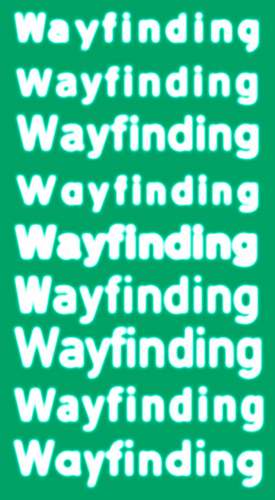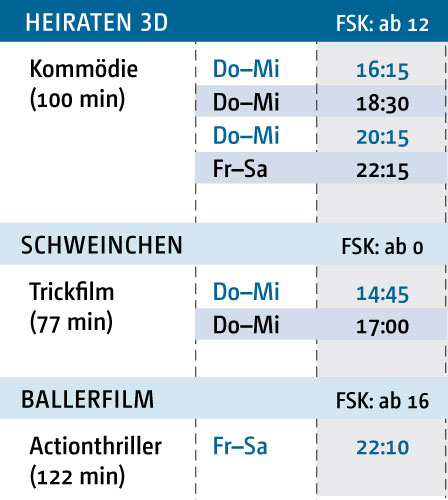
Phänomen Alterssehschwäche
Inwiefern muss man die Standardfloskel berücksichtigen, die bei jeglicher Art von Text unter 10pt wie aus der Pistole geschossen kommt?
»Aber die Älteren können das ja gar nicht lesen!«
Können ältere Menschen oft wirklich schlechter Text erkennen, oder müssen die einfach nur mal wieder zum Optiker? Ich kann mich da irgendwie schlecht reinversetzen. Das Gehirn verarbeitet die optischen Informationen doch genauso wie bei einem 20-Jähirgen – würde ich mal behaupten.
Natürlich kann der Text einmal kleiner wirken, wenn man stärkere Gläser hat – aber das betrifft ja nicht nur die Senioren.
Ich möchte zum Beispiel unsere Kinoprogramm-Handzettel komplett umstrukturieren in Tabellenform, also jede Spielzeit für jeden Tag einzeln aufführen. Gesetzt in Univers Condensed auf 8pt. Immerhin muss ich auch fast 250 verschiedene Spielzeiten unterbringen bei bis zu 20+ verschiedenen Filmen (variiert natürlich).
Ich bin auch schon sehr zufrieden. Vorher wurde alles abgekürzt wie
»tägl. 14:45, 16:45 & 18:45 Uhr, Mittwoch nur 15:45 Uhr!«.
Sieht nicht nur etwas unelegant aus, sondern führt auch zu Missverständnissen, da die Kinospielwochen immer Donnerstags anfangen, nicht Montags. Aber es hagelt natürlich bedenken, dass die älteren Leute das nicht erkennen können.
Ich habe mich dazu noch nicht konkret geäußert und will auch nicht unbedingt draufhämmern, dass die Senioren ohnehin keine relevante Zielgruppe darstellen. Würde lieber die Bedenken aus dem Weg räumen.
Barrierearm gestaltete Printprodukte sind nicht eindeutig definiert. 8 pt. condensed ist aber definitiv zu kleinteilig für Leute mit Altersweitsichtigkeit. Es gibt Brillen, die diese Sehschwächen simulieren können, das könnte dir helfen. Ich habe die Erfahrung gemacht, dass offene Buchstabenformen wie bei Lucida Sans gut gehen, wenn sie nicht zu knapp gesetzt werden und die Seite eine übersichtliche Struktur hat. Wer Schriftgrößen unter 10 pt nicht lesen kann, wird eh ein Hilfsgerät zu hause haben, also bist du in dem Korridor gut aufgehoben. Bei >10pt springen sogar die meisten Normalsichtigen ab, weil es nicht gut lesbar ist.
Die Stadt Münster hat hierzu einen Ratgeber herausgegeben:
Das Gehirn verarbeitet die optischen Informationen doch genauso wie bei einem 20-Jähirgen – würde ich mal behaupten.
Natürlich kann der Text einmal kleiner wirken, wenn man stärkere Gläser hat – aber das betrifft ja nicht nur die Senioren.
nur sieht man als "fehlsichtiger" nicht dinge schlicht kleiner. sondern beispielsweise unschärfer. guck mal in den autobahn-thread.
und stell dir das jetzt mal in 8 punkt vor... und damit hast du nur einen teil der fehlsichtigkeiten abgedeckt. ich hab tage, da werden die einzelbilder der augen nicht korrekt zusammengerechnet. dann seh ich nicht nur unscharf sondern auch gleich noch doppelt.
also bittebitte nicht zu klein setzen :)
Wobei ich den Simulator von optiker.at nicht so gut finde. Hab den grade getestet, und ich sehe nicht so wie der behauptet (-6.0).
Ich habe mal ein paar Beispielsätze zusammengewürfelt und zur Ansicht hochgeladen, falls es jemanden Interessiert.
Dann sieht man auch gleich die argen Schwachstellen an diversen Ecken.
Hab ja noch ganz andere Probleme damit :mrgreen:
Durch die unterschiedlichen Spielzeiten pro Tag und Film fällt natürlich auch die Größe von einem Block unterschiedlich aus. Wobei ich hier einfach ein buntes worst-case-Szenario zusammenschmissen habe, wo hinten auch mal mehrere Spielzeiten auftauchen (gibt immer eine feste Reihenfolge, neueste Filme zuerst) – ist in der Regel nicht so. Kommt aber vor.
Auf jeden Fall sollten die Filmtitel über alle drei Spalten jeweils auf gleicher Höhe anfangen, sonst ist das das reine Chaos.
Ich muss noch überlegen, wie ich es aufteile, aber eine feste Zeilenanzahl pro Filmblock wäre zugunsten der Übersicht natürlich vorteilhaft. Führt aber zu Platzproblemen, wenn z.B. zu Weihnachten über 20 verschiedene Filme laufen, Spitzenkandidaten laufen auch schon einmal mit 10 verschiedenen Spielzeiten pro Tag an (=11 Zeilen), während andere nur 1 oder 2 Spielzeiten haben. Wobei ich noch nicht dazu kam, den Satz mit reellen Spielzeiten zu testen, was vielleicht von Vorteil wäre. Normal (aber nicht immer) haben die neuen Filme ja die meisten Spielzeiten, die älteren immer weniger, bis Sie irgendwann rausfliegen.
Aber so wild, wie das jetzt aussieht, kann es natürlich nicht bleiben, ist klar.
Schwierig, schwierig. Größeres Papierformat fällt übrigens flach. Wenn ich *dieses* Format auf den Nutzen setzte, bekomme ich 4 Blätter auf einen Druckbogen an der Digitaldruckmaschine. Bei DIN A4 sind es gleich nur noch 2 – das sprengt den Kostenrahmen.
Und dass der »Kalender« nach Kinozeitrechnung Donnerstags anfängt muss ja auch noch besser ausgezeichnet werden.
Nur auf den ersten Blick: Das größte Problem ist m.E., daß Du eine gigantische Redundanz der Informationen erzeugt hast. Für die Mehrzahl der Filme wird für jeden Slot 7-mal die gleiche Zeit gezeigt. Du würdest schon eine ganze Menge Platz schaffen, wenn Du die Redundanz in die Wochentage auslagerst, also die Angabe Do–Mi und dann jeweils nur eine Zeitangabe. Spezielle Angaben ließen sich so ja noch immer realisieren, Du brauchst aber nur 2/7–3/7 des Platzes, das Ganze wird dafür größer und übersichtlicher.
Wir sind hier ein Multiplex, das keiner Kette angehört. Bei sieben Kinosälen recht seltenes Phänomen eigentlich. Heißt natürlich auch, dass bei uns noch viel in Eigenregie gehandhabt wird. Handzettel sind bei uns generell sehr gefragt. Teilweise stehen die Dienstags eben auf der Matte und möchten das Programm für die nächste Spielwoche (liegen nicht mal in der Nähe einer Fußgängerzone). Die Anfrage ist sogar dermaßen groß, dass ich künftig bis zu 15 Verteilstätten in den umliegenden Ortschaften organisieren muss, sodass unsere Auflage nochmal nach oben explodiert. Aber auch wenn ich über den Tellerrand schaue zu den zwei Plexen in der nächsten Großstadt, haben die wöchentlich eine verhältnismäßig vergleichbare Auflage. Kurzum: Mit Verteilstellen peile ich knapp 2.000 Zettelchen pro Woche an. Digitaldruck. Teurer Spaß – deswegen habe ich auch ein so kurioses Format ausgerechnet. Von diesem Folder wie in der PDF würde ich auf eine DC 240 (die ich gerne hätte :hammer: ) immerhin 4 Stück auf einen Bogen bekommen. Ohne Schnittmarken, aber immerhin 3mm Anschnitt. Das amerikanische Papierformat machts möglich. :party: